Font Berbentuk Balok dan Kotak | Assalamualaikum, halo sobat grafis-media. pada pertemuan kali ini, saya mau memberikan 15 Font Keren Bergaya Balok. semua font dibawah bisa di download secara gratis melalui situs resminya masing-masing. terdapat 2 versi yakni, versi 2d dan 3 dimensi. silahkan pilih sesuai tema desainnya yah.
Font Balok 2D
1. Font Balok High School Usa
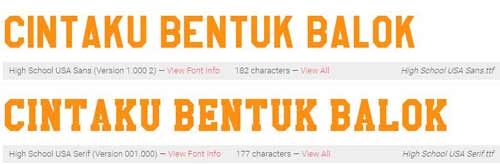
2. Qui Finn Font
Font Balok 3D
Berikut ini koleksi font bergaya balok 3d. dasar bentuk dari semua font ini adalah kubus yang memiliki volume. sangat cocok dipadukan dengan desain berilustrasikan 3 dimensi.
1. Font Bad Mofo | Download
2. Minecraft Pe Font
3. Font Letterblock
4. Blus Block
5. Ft Scandinaviantitan Font
6. Font Pez | Download
7. Boxing Brophius
8. Cubox 3d Font
9. D3 Concretism